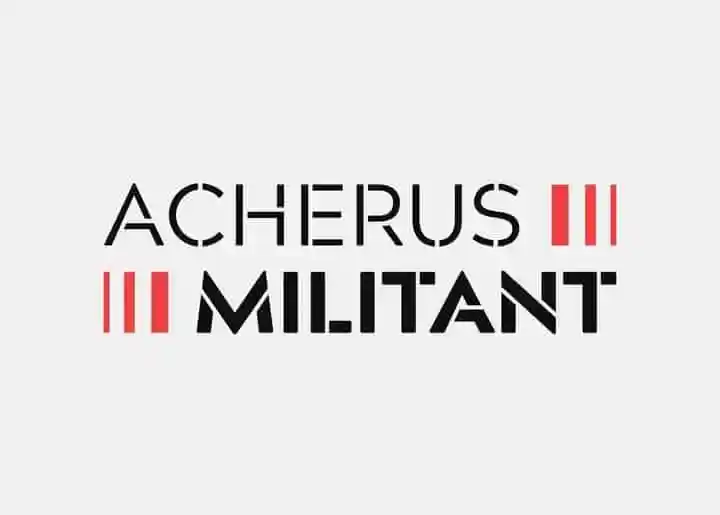
Acherus Militant Sans Serif Font Demo – Download Grátis
Acherus Militant Sans Serif é uma fonte elegante e minimalista criada para designers que valorizam estilos limpos e modernos. Esta opção se destaca pela sua simplicidade, fornecendo soluções flexíveis para projetos de identidades visuais. Feita pelo designer de fontes Horizon Type, Acherus Militant Sans Serif é perfeita para a criação de marcas de palavra, títulos e lemas, proporcionando um visual clean e minimalista que se destaca em qualquer projeto gráfico. Seja para logotipos ou websites modernos, esta fonte é uma escolha inteligente para quem procura um estilo inconfundível. Adicione seu próprio toque de criatividade com as várias versões alternativas disponíveis na Acherus Militant Sans Serif. Experimente essa opção e inspire-se em criações futuristas.